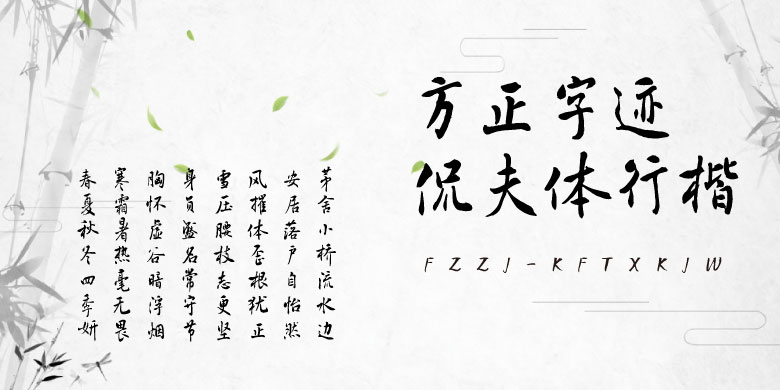
方正字迹-侃夫体行楷
字体介绍:
方正字迹-侃夫体作者李志强,字库的创意体现了“雅俗共赏的审美追求,集古出新的艺术品质,清新自然的表达风格,遵章循法的书写规范。”作者曾出版书法理论著作《中国书法二十六讲》、自作诗词书法集《啸余诗草》、古体诗词《山前诗稿》。书法多次参加河南及全国书法大赛,曾获河南省行草展一等奖,入选首届中国书法“兰亭奖”、首届“杏花村杯”电视书法大奖赛。四十余年遍临百家,博观约取,追求字的味道、含蕴、意象与亲和力,结字守中正,行笔趋灵活,做到了百姓喜欢,方家同钦。